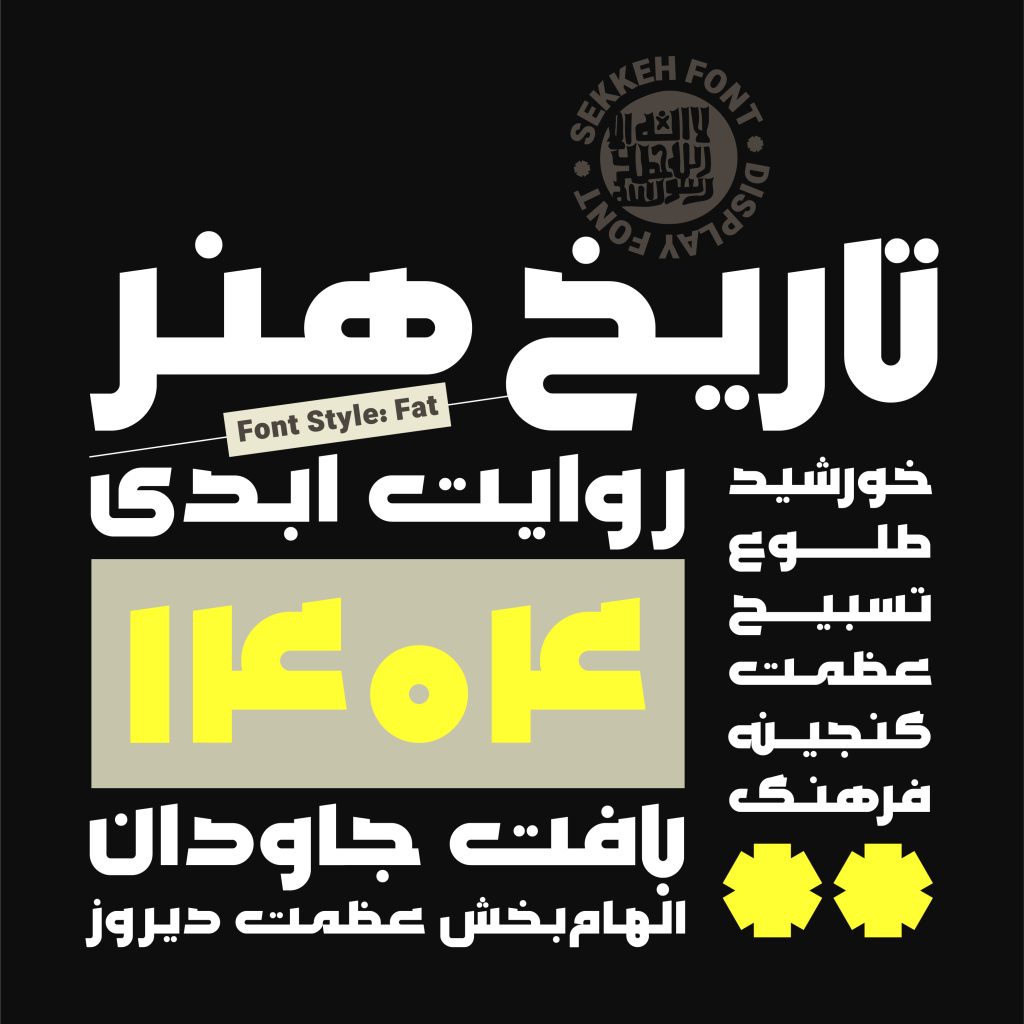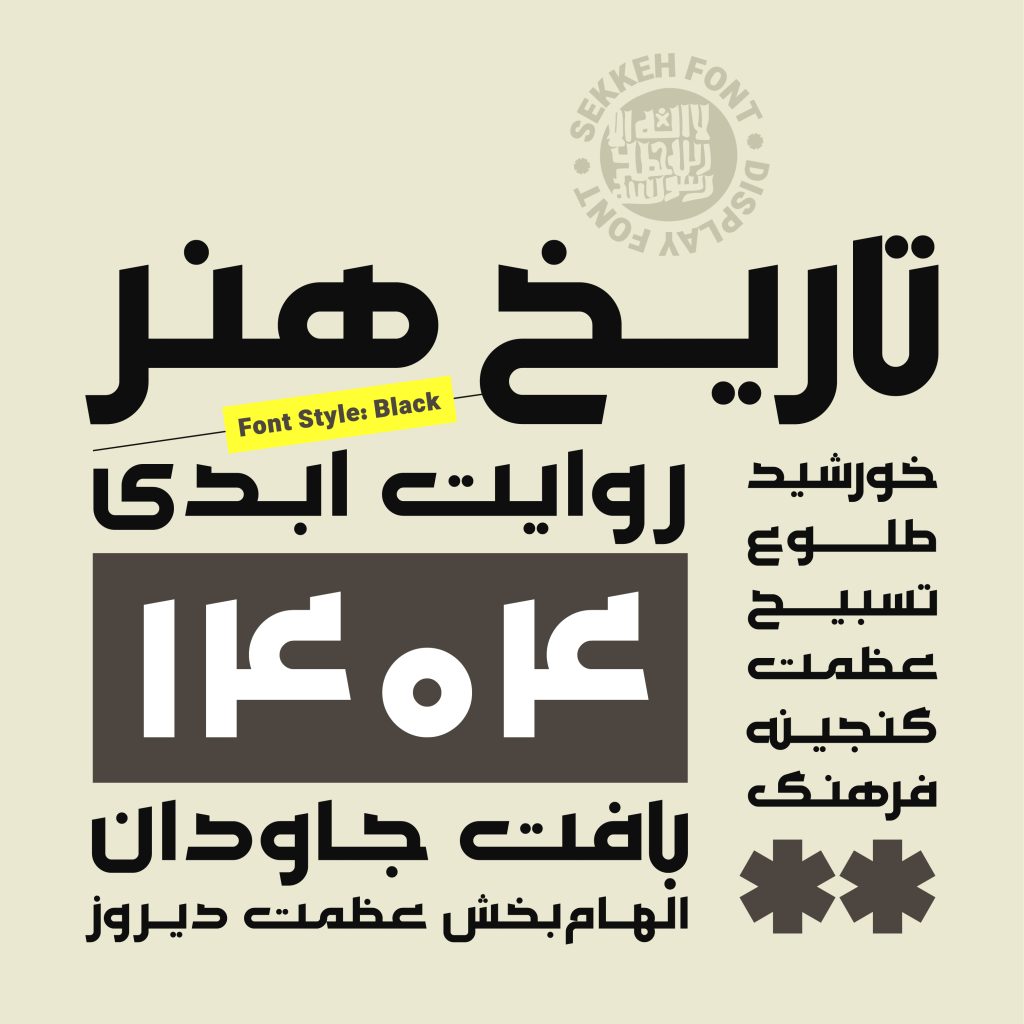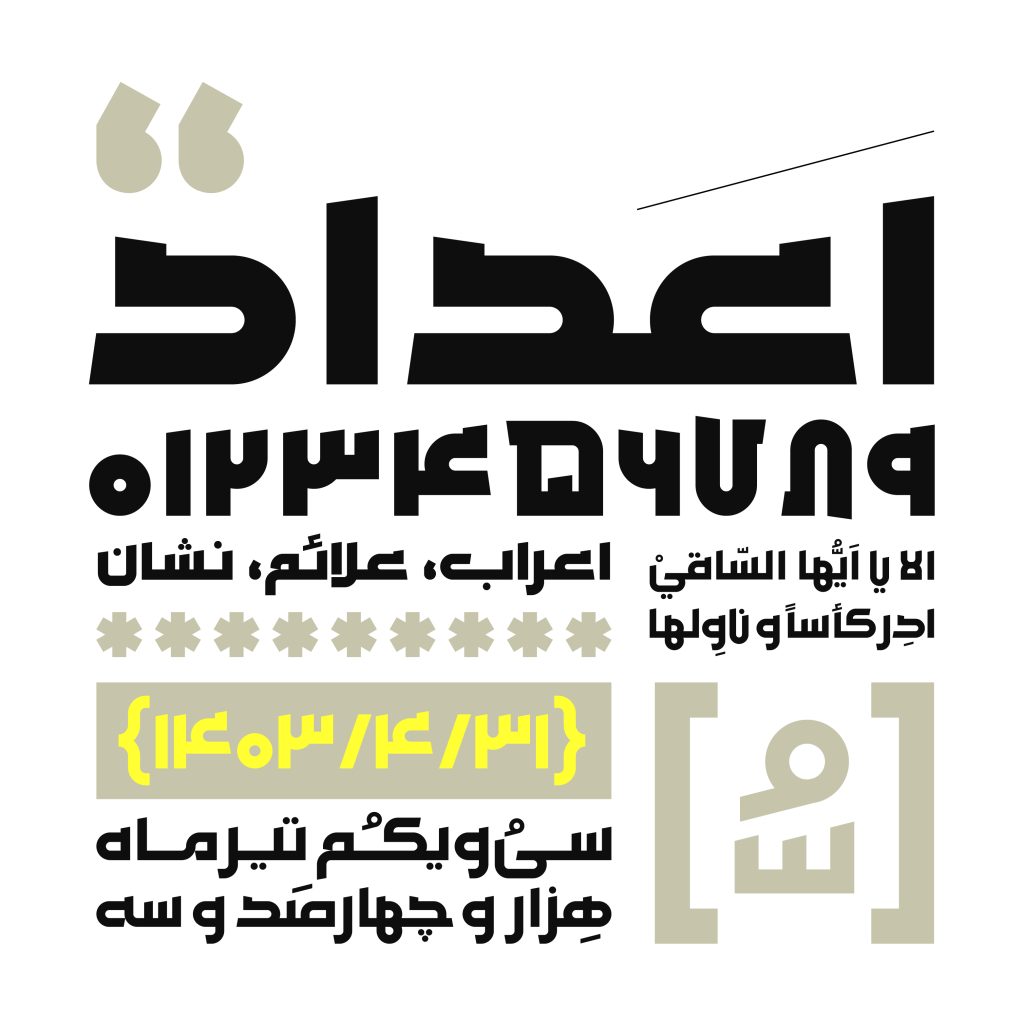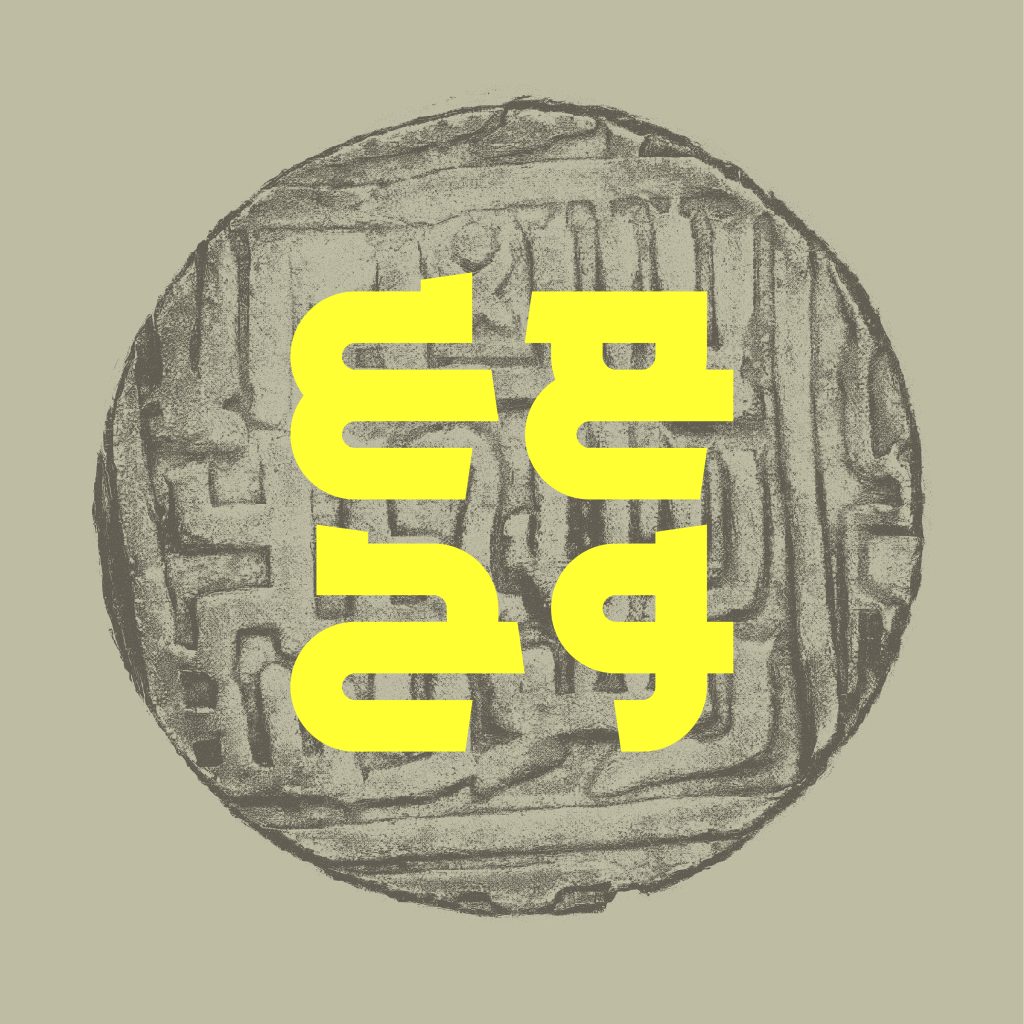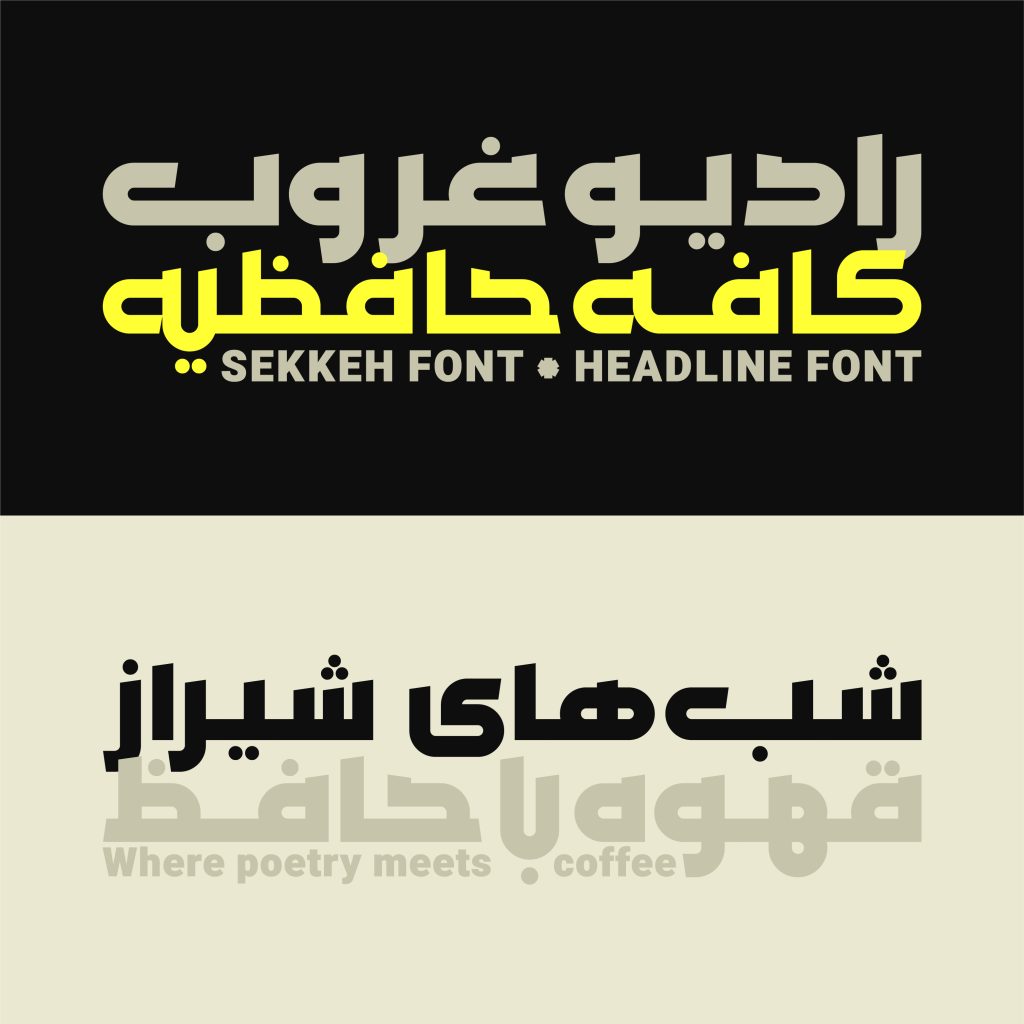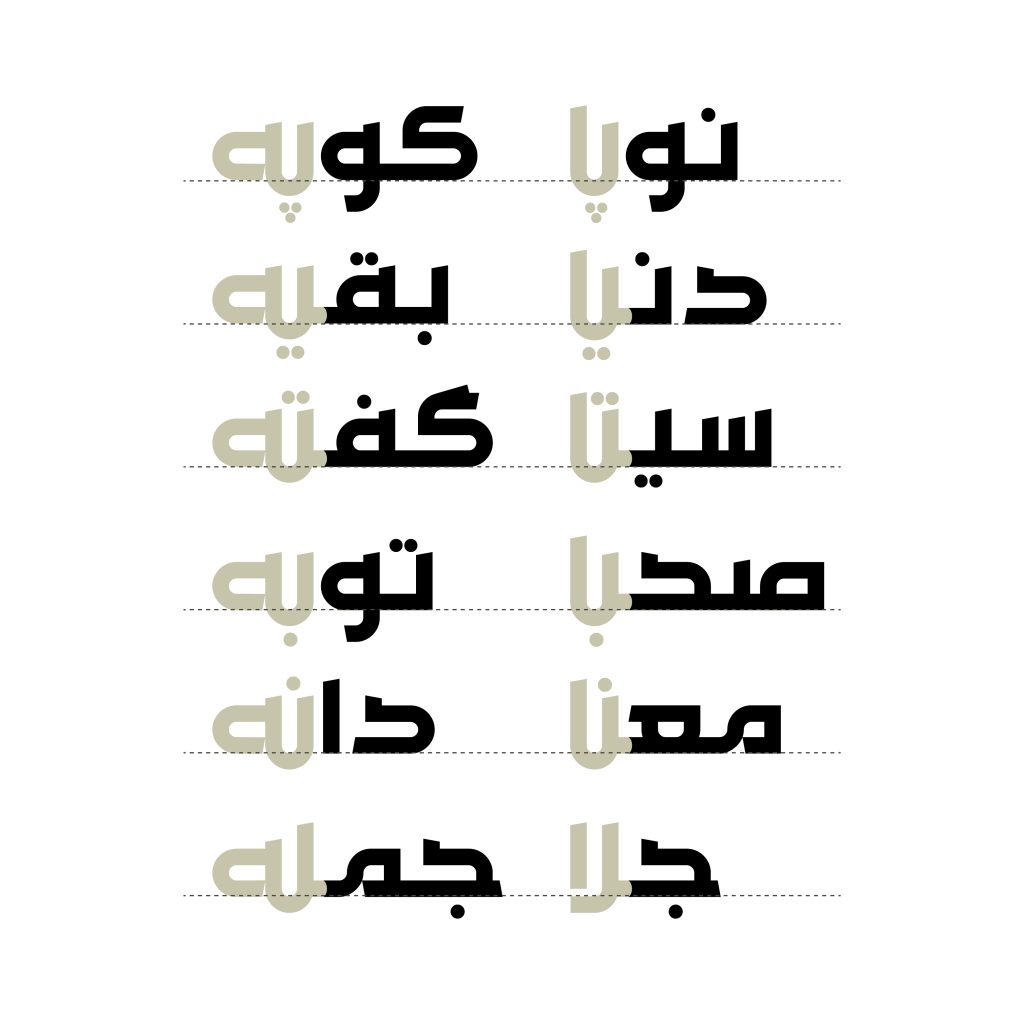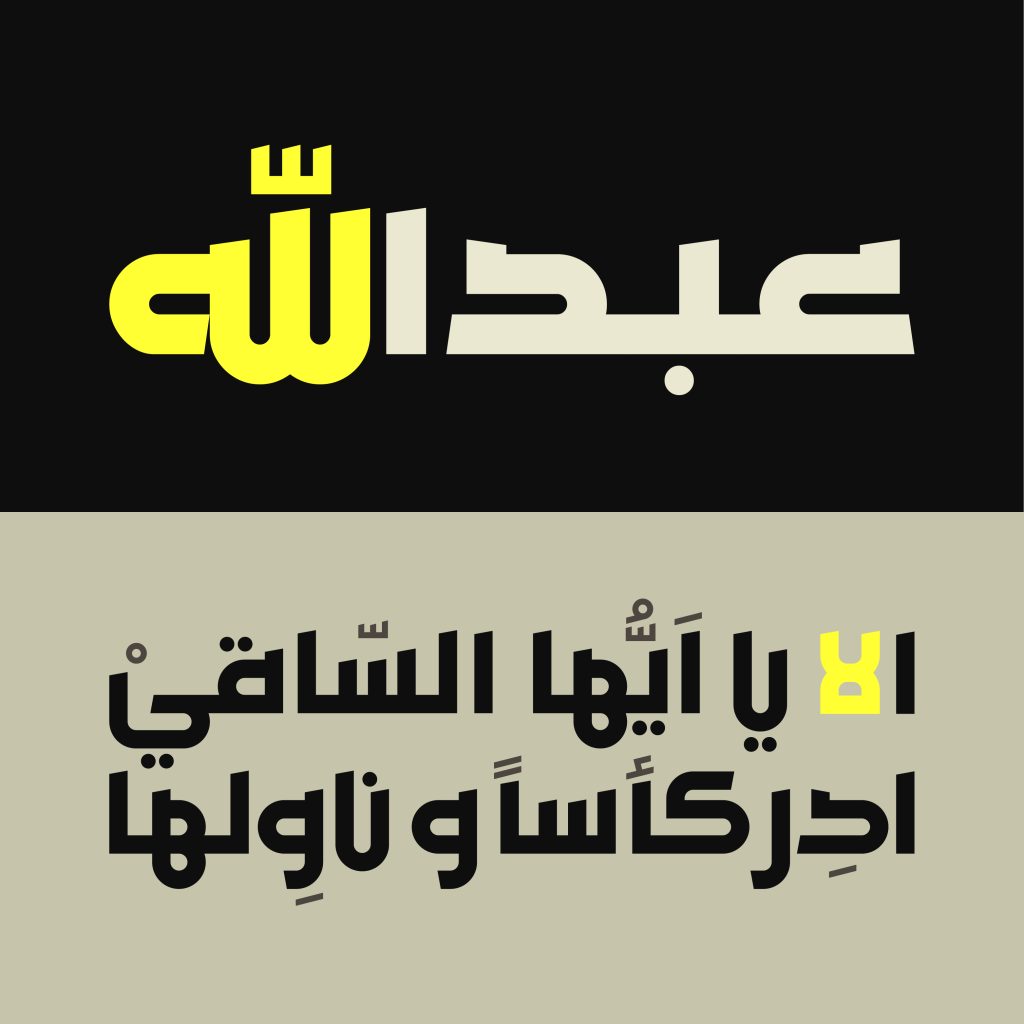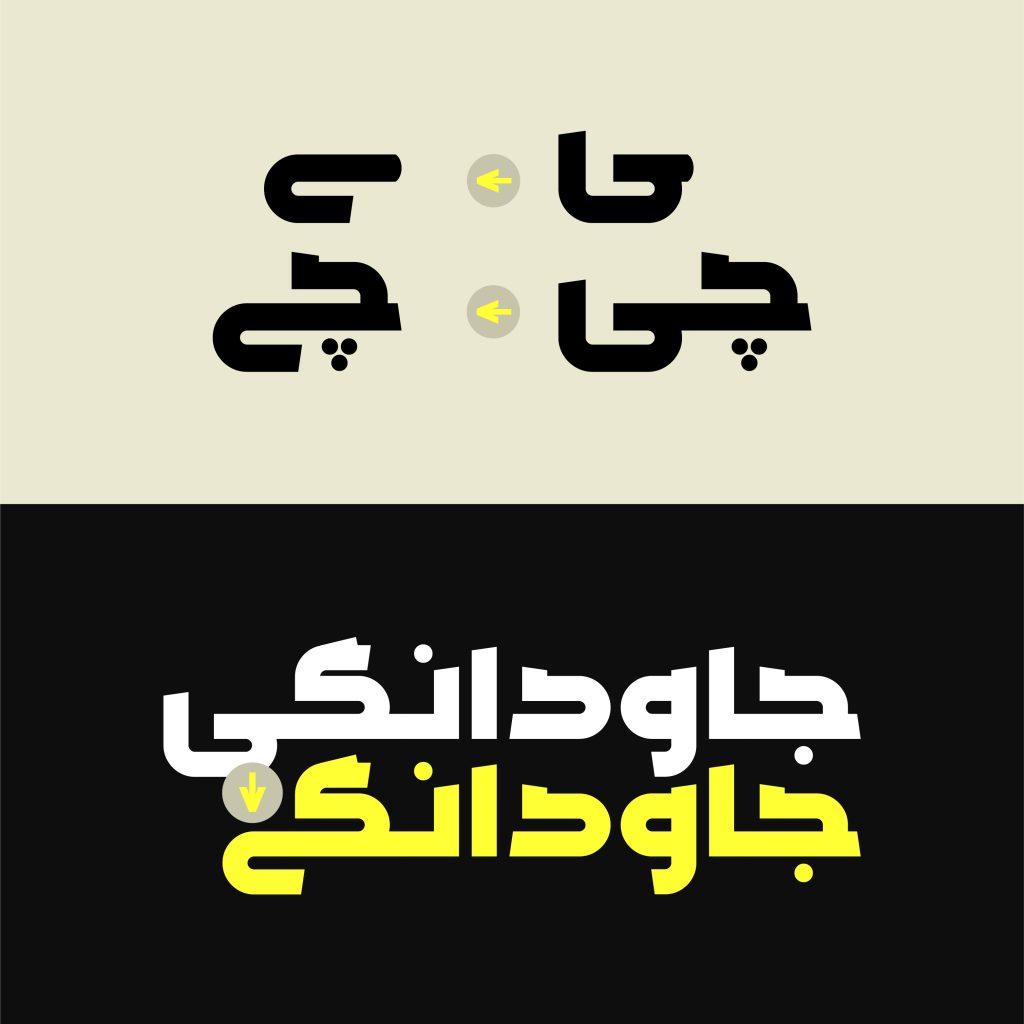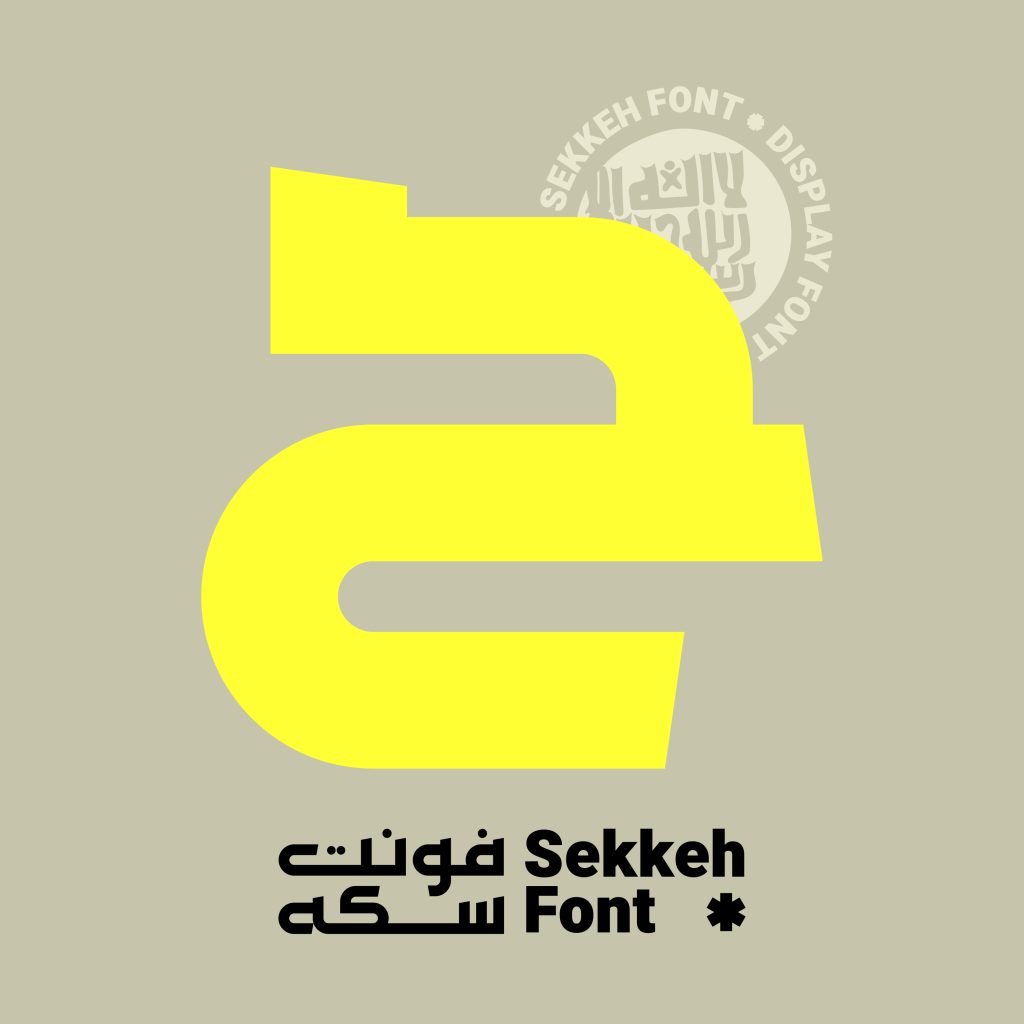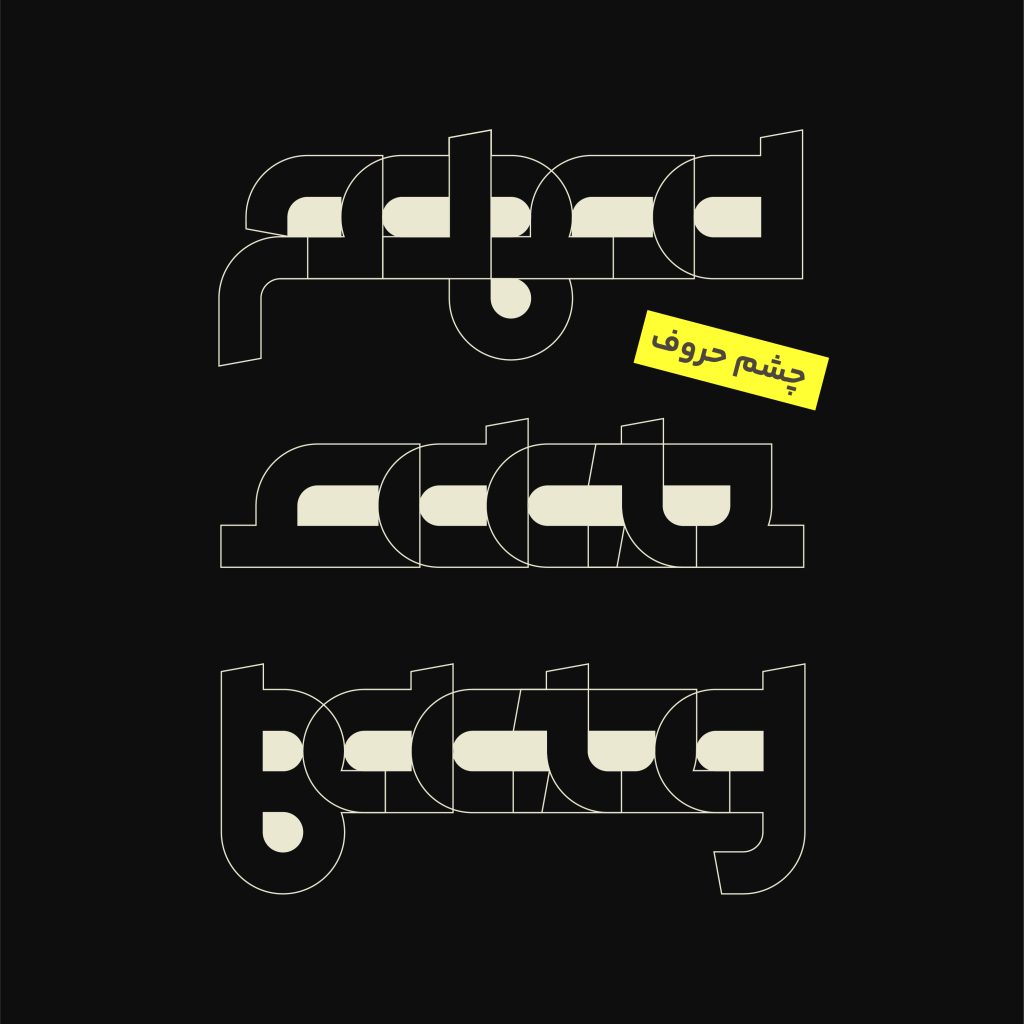
فونت سکه
فونت سکه حاصل نگاهی دوباره به نقشها و خطوط حک شده بر روی سکههای تاریخی است؛ جایی که خوشنویسی، هویت و قدرت در دایرهای کوچک به نمایش درمیآمد. این فونت تلاش میکند همان صلابت، نظم هندسی و ماندگاری را به حروف فارسی بیاورد. ساختار زاویهدار و تقریبا بنایی آن، یادآور سنت کوفی است؛ اما در عین حال با بیانی تازه و معاصر بازآفرینی شده است.
این فونت برای تیترها و عنوانهای شاخص طراحی شده است؛ جایی که نیاز به حضوری قاطع و ماندگار داریم. سکه ساده است اما غریب نیست، آشناست اما تکراری نه؛ بازتابی از تاریخ که با زبان امروز سخن میگوید.
پشتیبانی تایپ فیس سکه از زبان های مختلف
تایپ فیس سکه از زبان های بسیاری پشتیبانی می کند از جمله این زبان ها می توان به زبان های فارسی عربی،انگلیسی اردو کردی و … اشاره نمود این تنوع از پشتیبانی گزینهای بیهمتا برای طراحان خوشذوق تایپوگرافی فارسی است تا توانمندی های خود را در قالب این قلم به تصویر کشند.
سکه در دو وزن Fatو Blackارائه میشود و برای تیترها و عنوانهای شاخص متولد شده است. ترکیب زوایای هندسی با سطوح نرم و یکپارچه، آن را برای کاربردهای گرافیکی، پوستر، جلد کتاب، برندینگ و پروژههای فرهنگی-هنری بسیار کرده است با تمرکز بر ساختار هندسی و قاطع کوفی طراحی و در این مسیر، اصول اساسی از جمله : لیگچرها و ترکیبات ویژه، تناسبات هندسی حروف، فضاهای خالی و چشم های حروف و سایر هماهنگی ها را مد نظر قرار داده است.